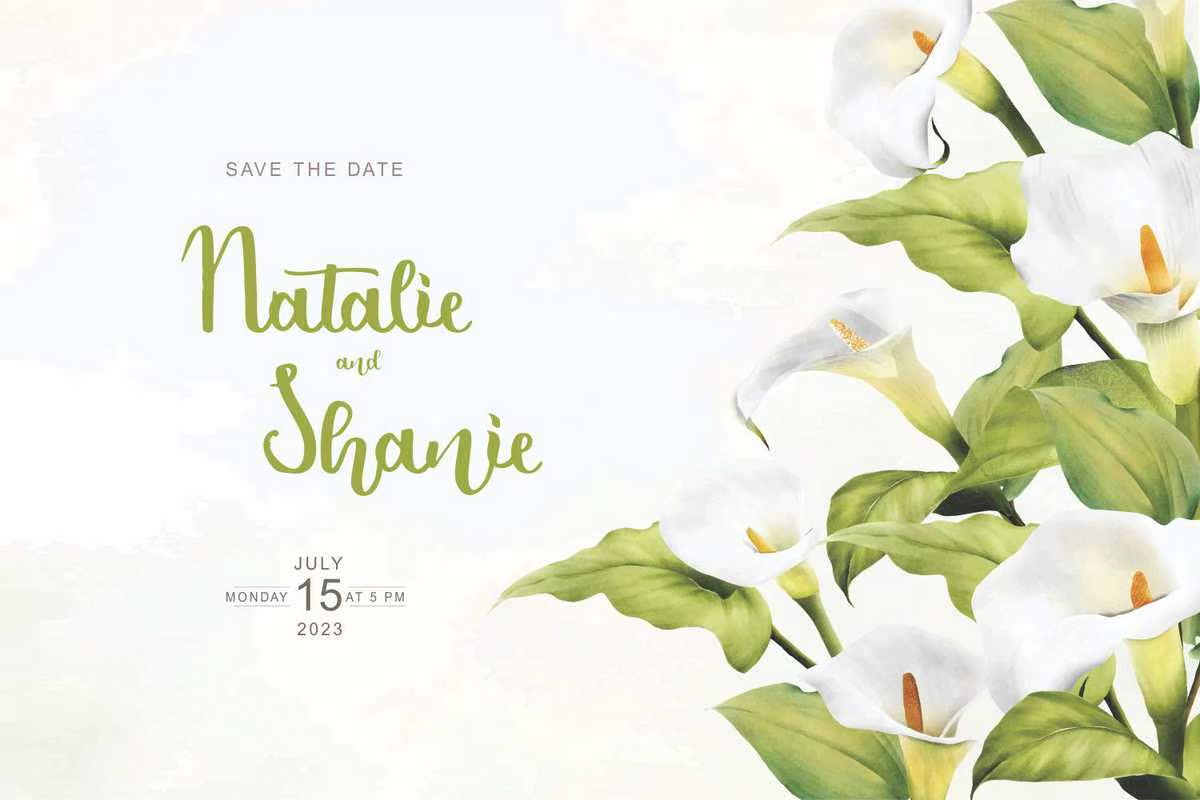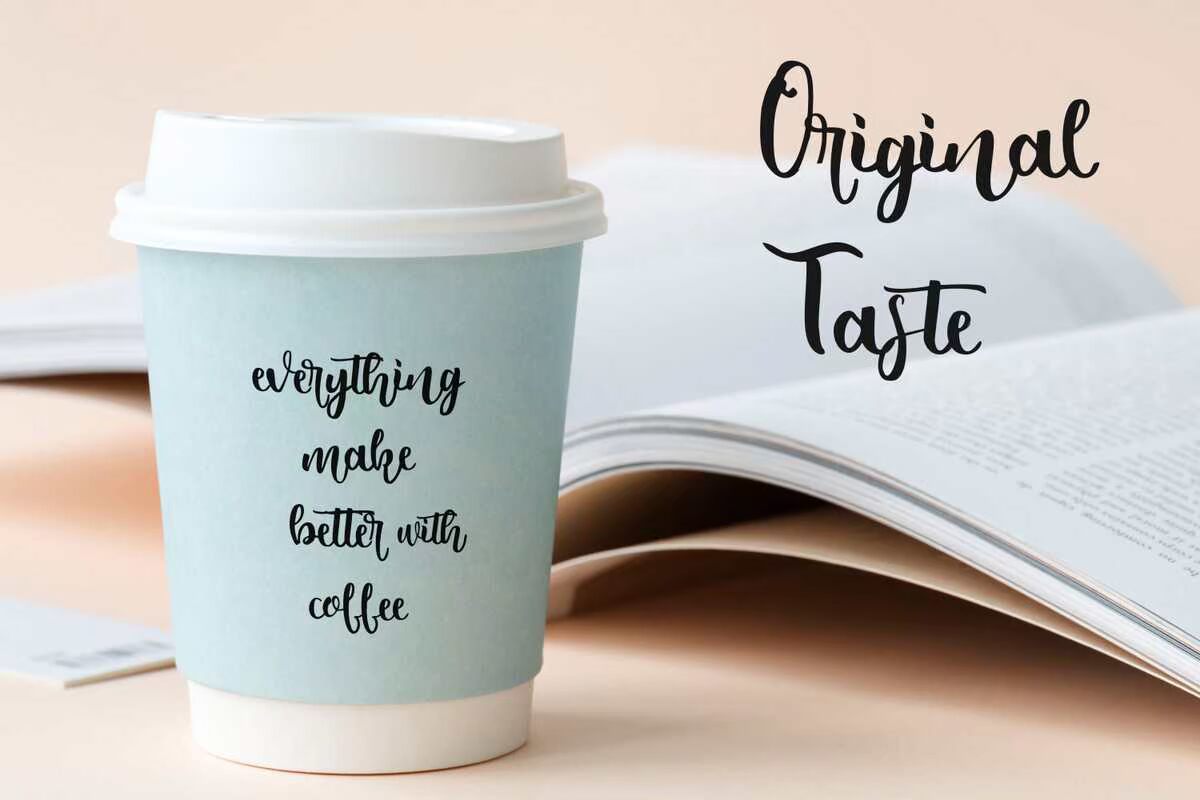
emelyblosomisafunadbouncyHandlitenFont。使用它可以让您的想法更加真实,并创建壮观的设计!这个字体是经过编码的,意味着你可以访问所有的符号和SWASHEASE!emelyblosomisafunadbouncyHandlitenFont。使用它可以让您的想法更加真实,并创建壮观的设计!这个字体是经过编码的,意味着你可以访问所有的符号和SWASHEASE!